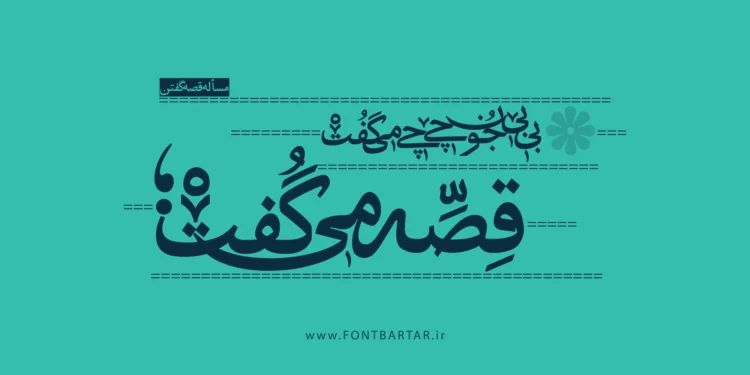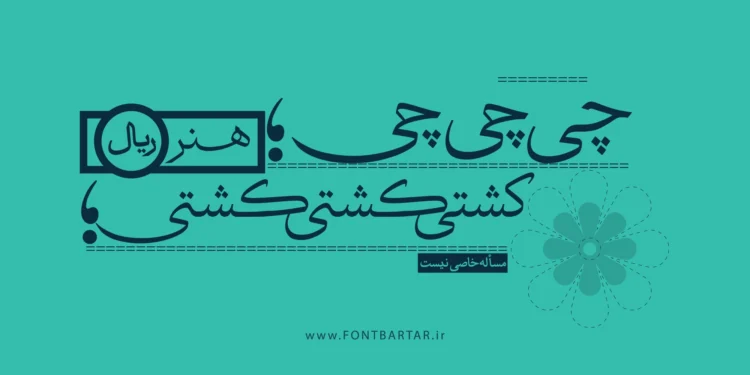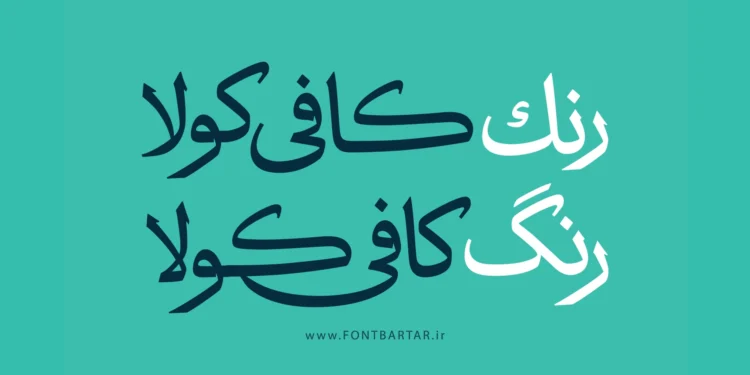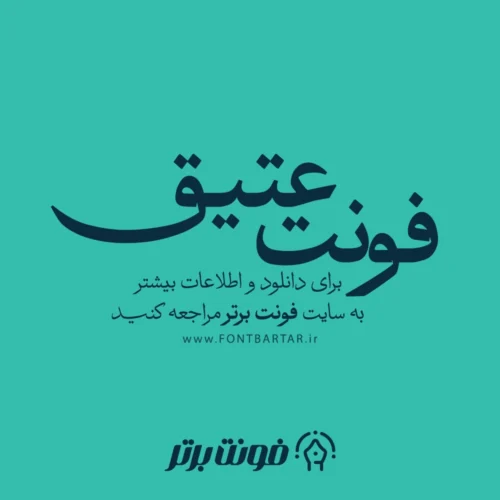
دانلود فونت عتیق
فونت عتیق برگرفته از طراحی حروف سربی چاپی روزنامهها و نشریات دهۀ 20 و 30 خورشیدی است. از یک سو به خط ثلث پهلو میزند و از سوی دیگر به خط نسخ. نخستین بار در سال ۱۳۹۶ در دوسالانۀ سرو نقرهای به نمایش گذاشته شد و در کتاب نمایشگاه به چاپ رسید.
فونت عتیق سه وزن دارد که هر وزن دارای ۸۷۳ ترکیب، حروف کشیده و جایگزین است. (این فونت در مجموع ۱۸۰۰ گلیف دارد.)
فونت جدید عتیق
فونت عتیق شخصیتی سیال و نوستالژیک دارد. این فونت در دهه 20 خورشیدی در روزنامههای ایران راه یافت و تا سالهای اغازین دهه 40 ادامه یافت.
در دیزاین این فونت تلاش براین بوده تا اشکالات فنی و زیباییشناختی فونت برطرف شود و لیگیچرهای مناسب و جدید برای آن طراحی شود. برای بسیاری از حروف، گلیفهای جایگزین طراحی شده است، این قابلیتها به شما قدرت انتخاب و ایجاد تنوع در تایپوگرافی را میدهد.